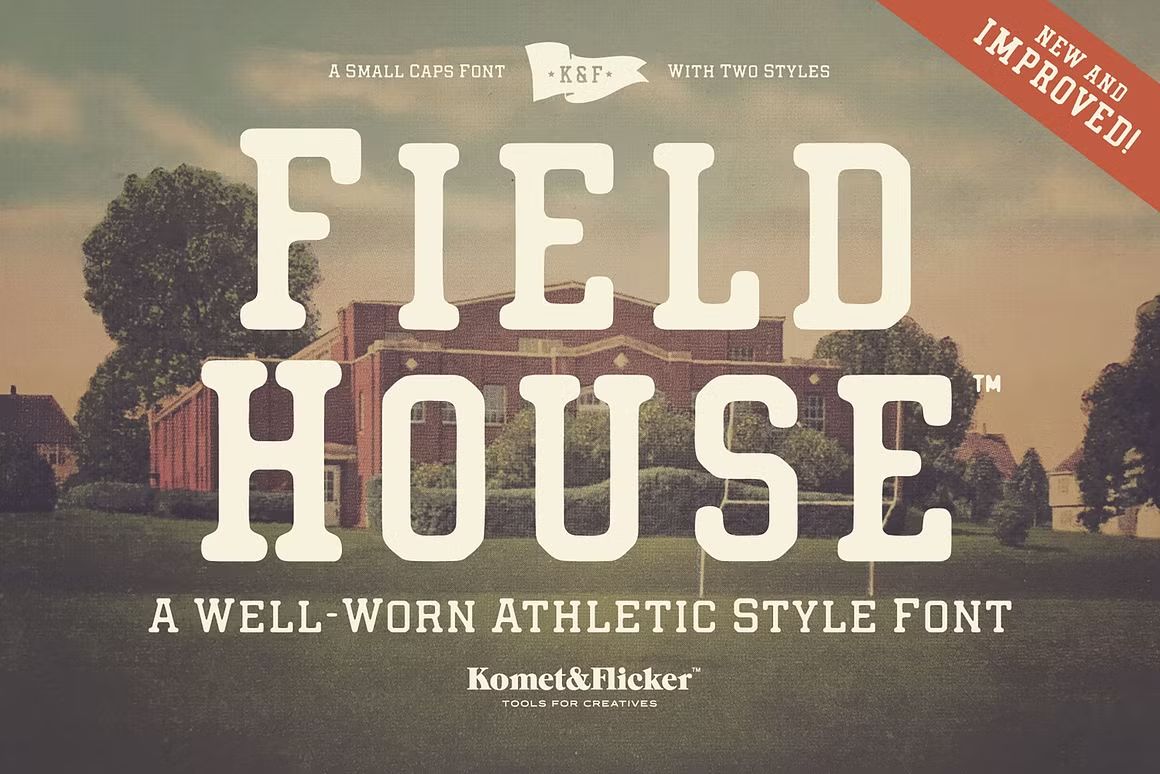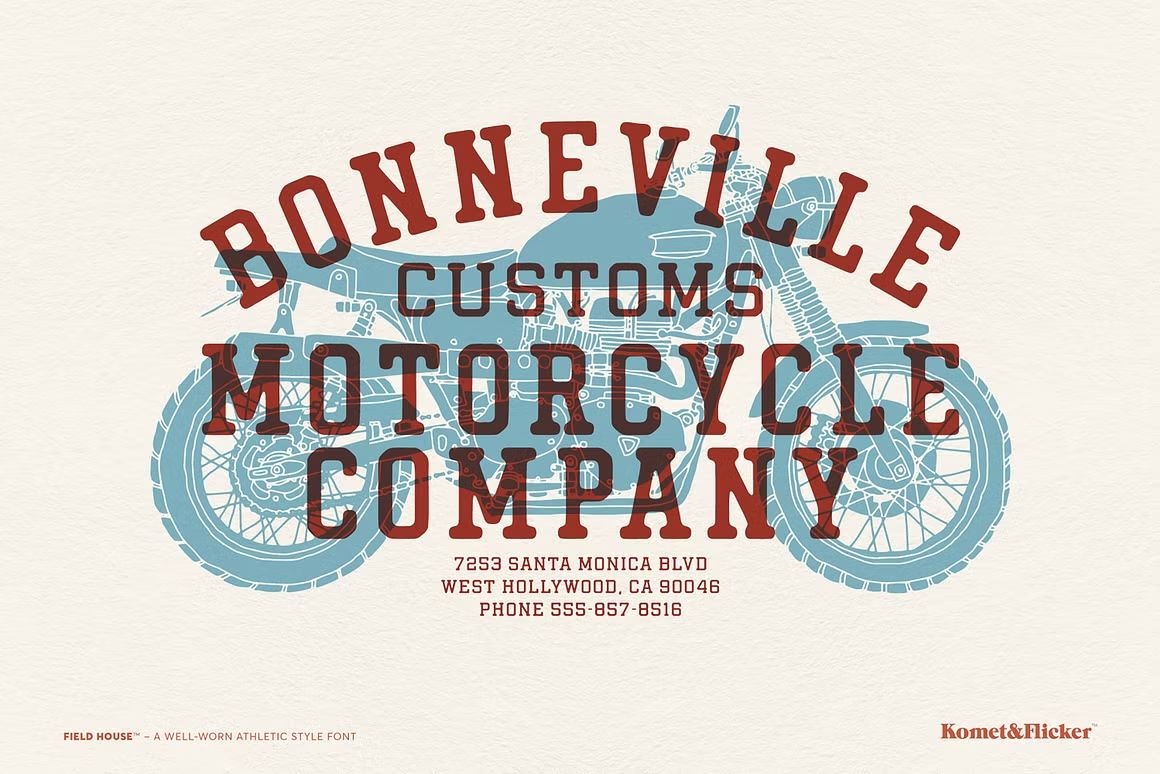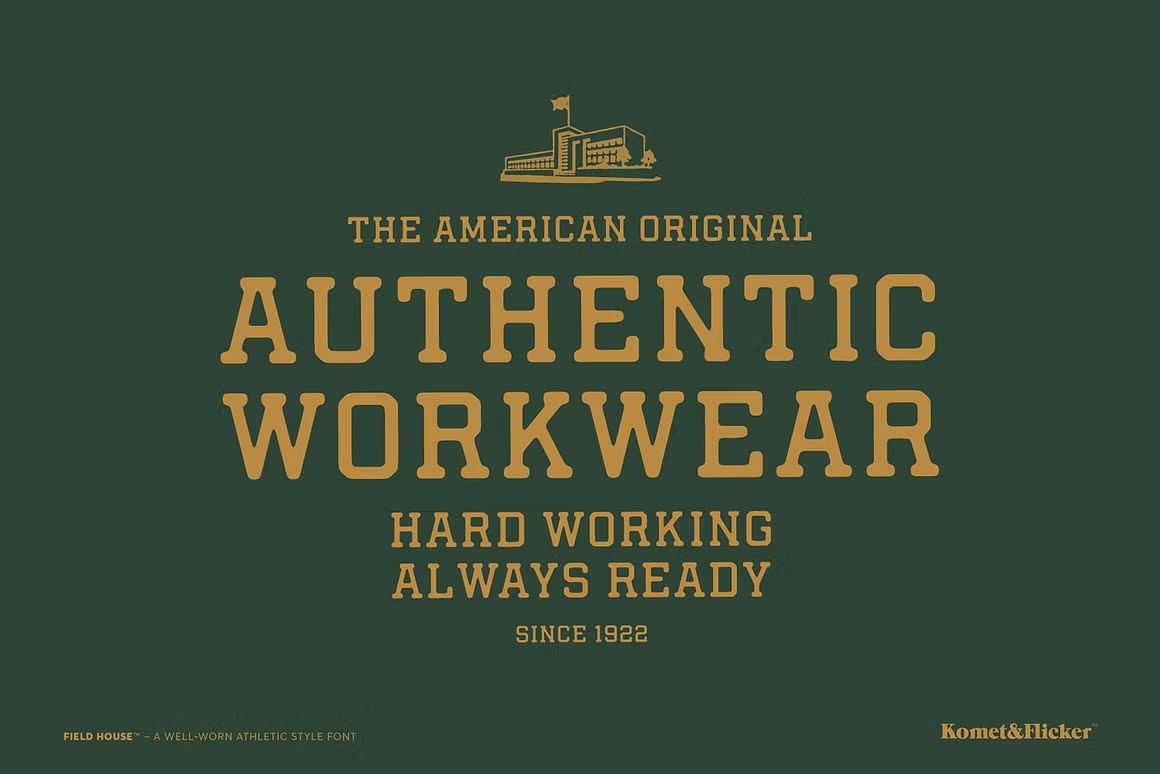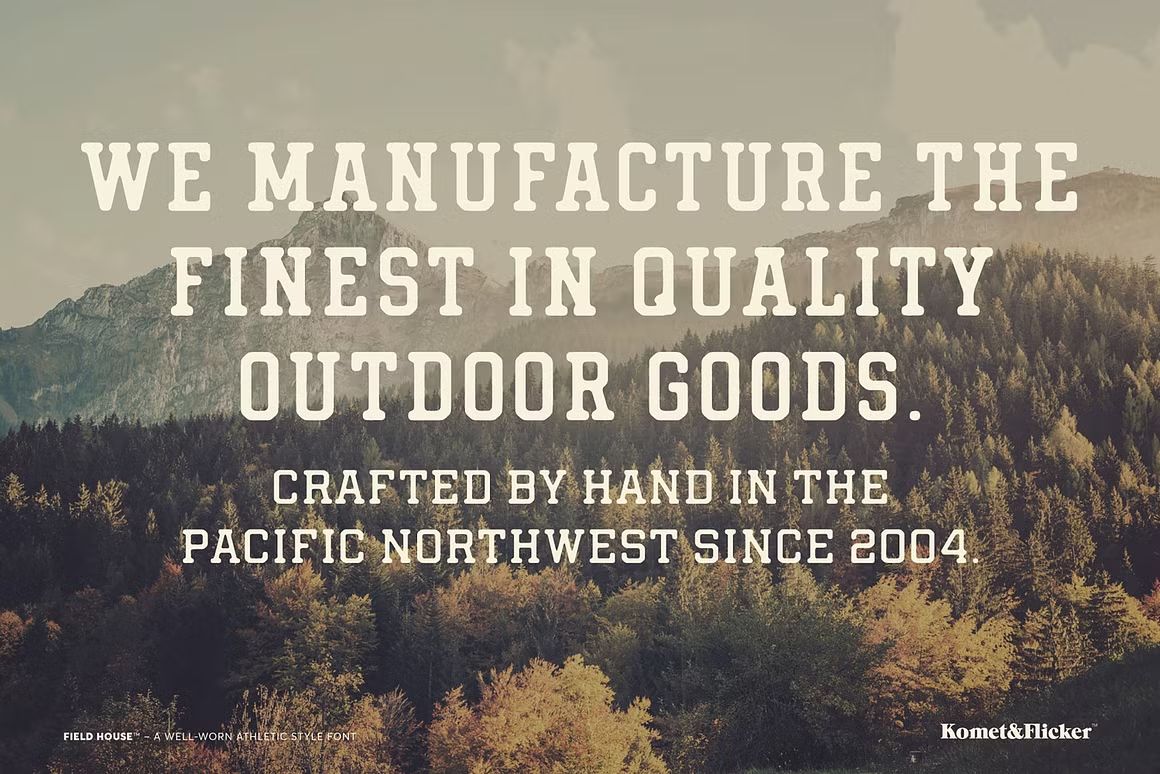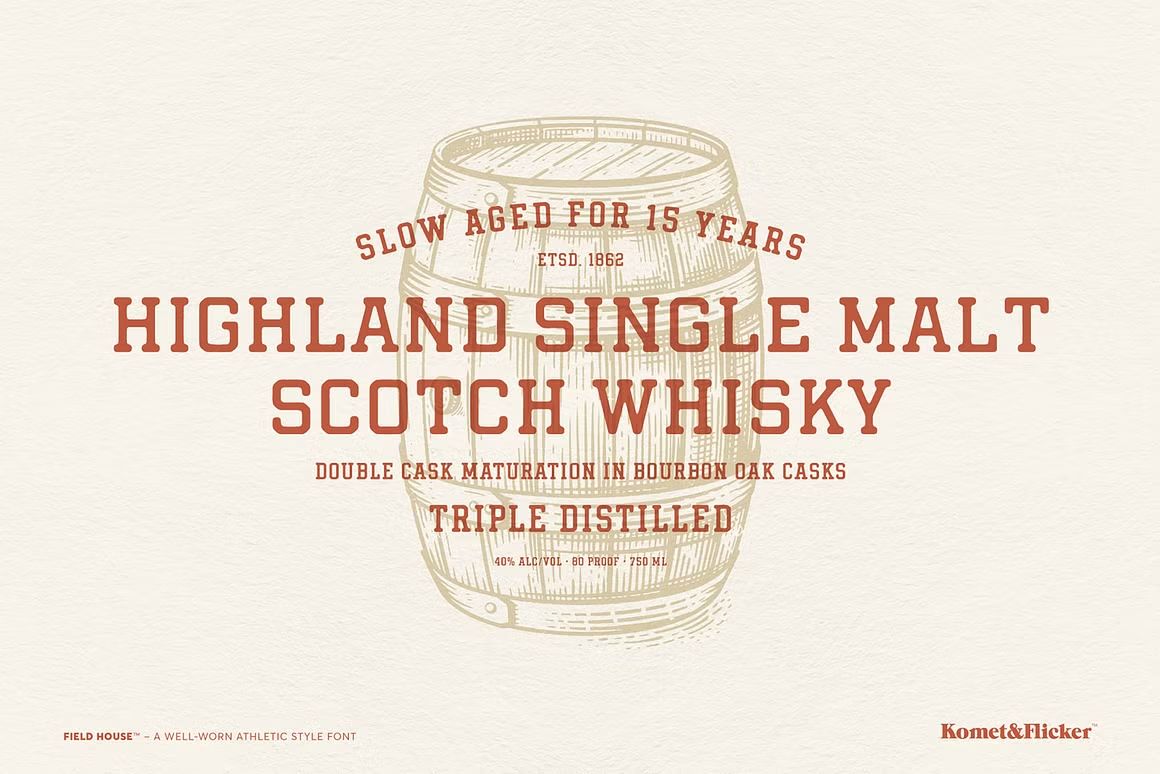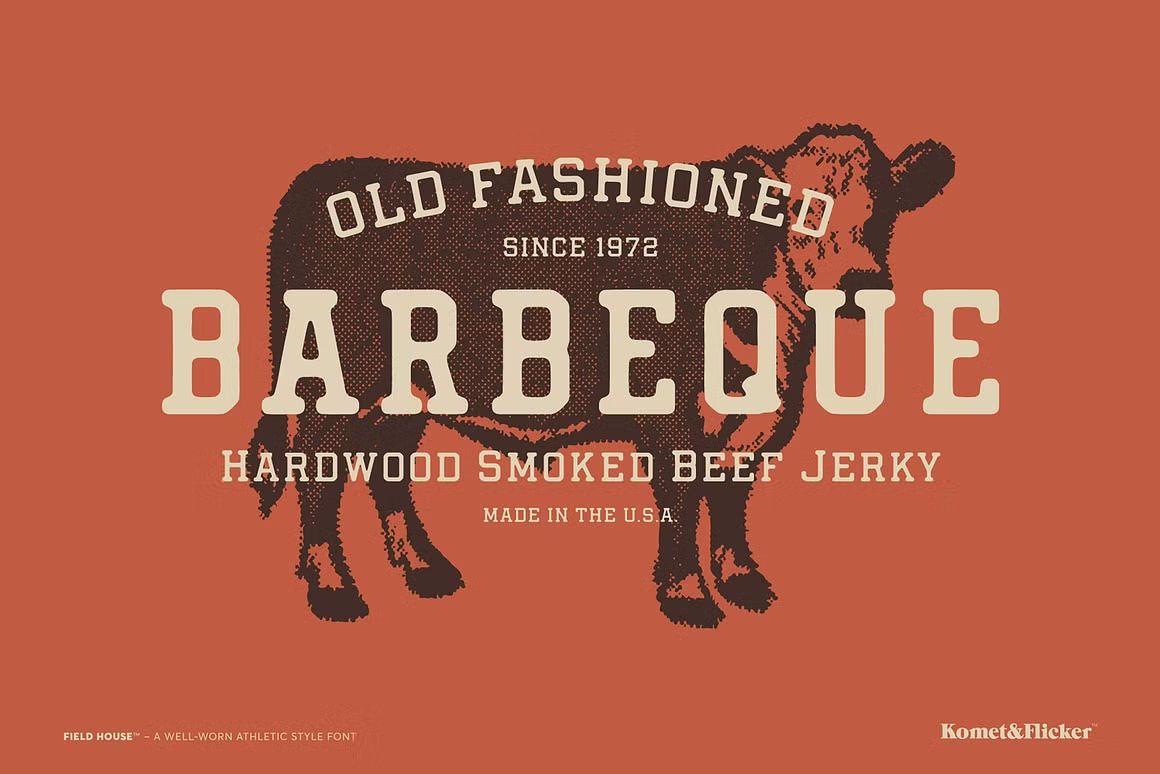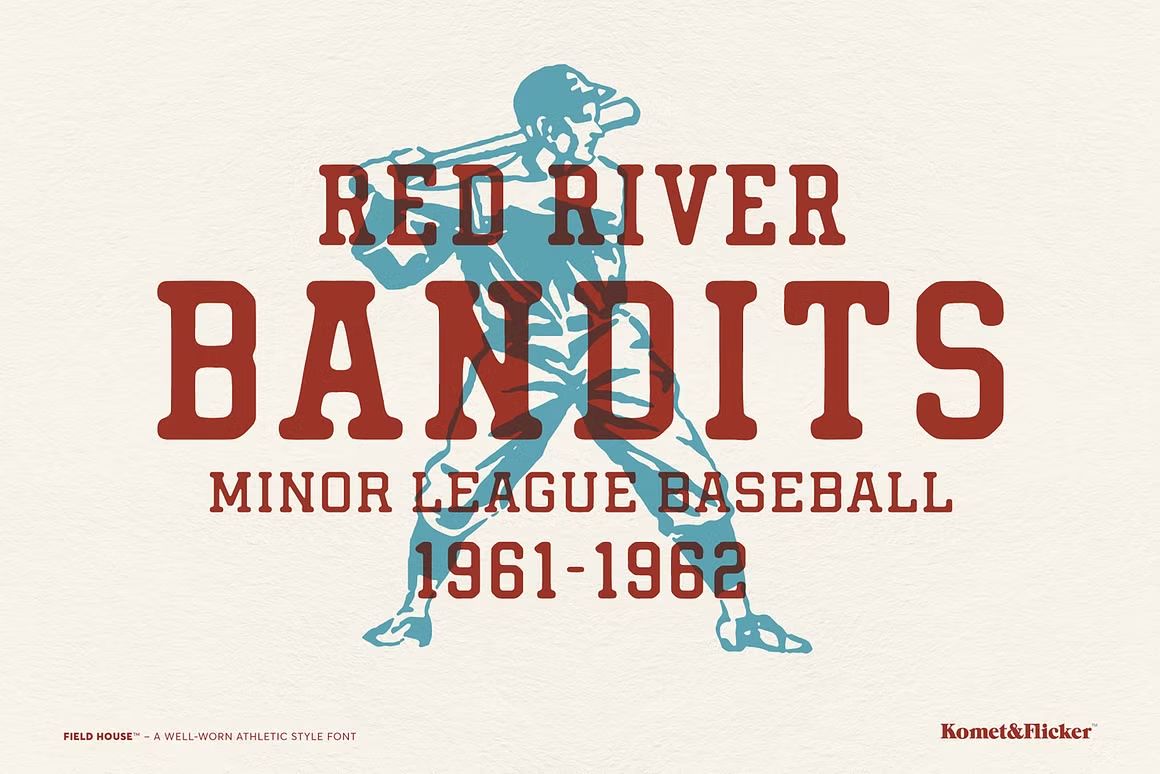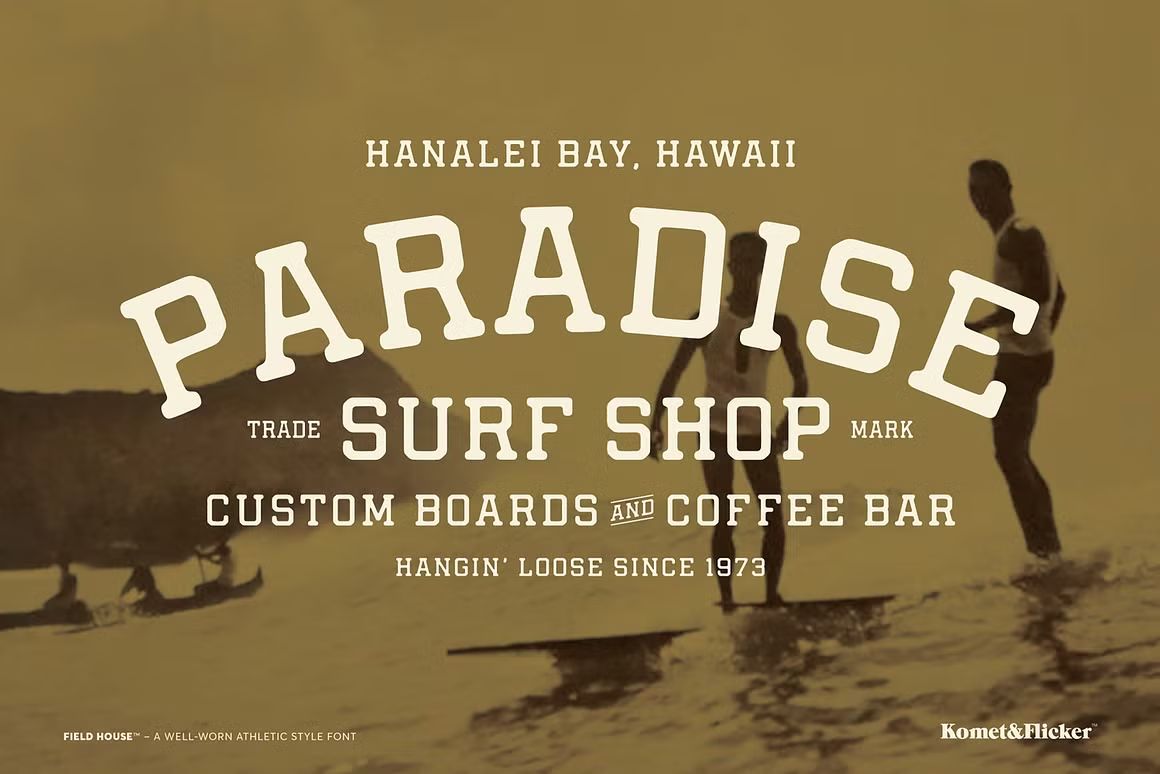
Field House – Sans Serif Font
Field House adalah font sans serif modern dan bersih, cocok untuk branding, editorial, dan desain minimalis. Format OTF/TTF/WOFF, siap digunakan di berbagai platform.
Field House adalah font sans serif bergaya modern dengan garis bersih dan struktur geometris yang kuat. Cocok untuk berbagai kebutuhan desain seperti branding, editorial, packaging, UI/UX, dan tipografi display. Font ini menghadirkan kesan profesional, minimalis, dan mudah dibaca, menjadikannya pilihan ideal untuk proyek desain yang mengutamakan kejelasan dan estetika kontemporer.
• Gaya sans serif modern dan serbaguna
• Cocok untuk branding, editorial, dan desain digital
• Termasuk huruf besar, kecil, angka, dan simbol